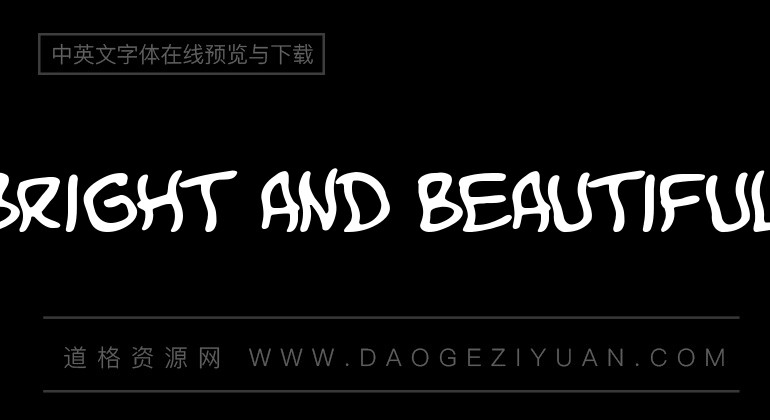
Bright and Beautiful
Bright and Beautiful 是一种手写风格的英文字体,它的字形流畅、轻盈、有一定的艺术气息,非常适合用于卡片、海报、标语等设计中,能够给人带来轻松、愉悦的感觉。 这种字体的特点在于它的字母之间有一定的距离,而且字母线条较为细长,有如同手写字的感觉。它的笔画有点类似于草书或楷书,但整体上却又显得比较随意和自由。 Bright and Beautiful 字体包含了大小写字母、数字、标点符号等常用字符,支持多国语言的文字编码。该字体适用于各种平面设计领域,如广告、包装、电子出版物、网站设计等,使得文字更加生动、有趣。
Bright and Beautiful是一款非常不错的手写艺术字体,具有很好的视觉感,适合于文化类的宣传设计、商业类品牌的广告和产品包装设计以及个性化文字排版等较多场景。
Bright and Beautiful字符映射图